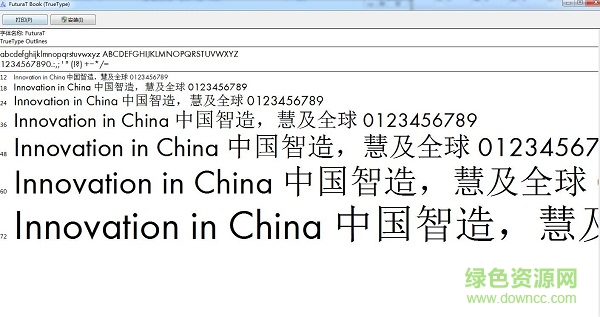
futurat-book字體是一款非常容易辨認(rèn)的幾何型無(wú)襯線字體,字形清脆干凈,字體轉(zhuǎn)折鋒利,眾多經(jīng)典logo都是通過(guò)這款字體設(shè)計(jì)而來(lái),喜歡的朋友快來(lái)下載吧!
英文文字大致分成三類(lèi),襯線體,無(wú)襯線體和其他字體。其他字體包括哥特體,手寫(xiě)體和裝飾體!